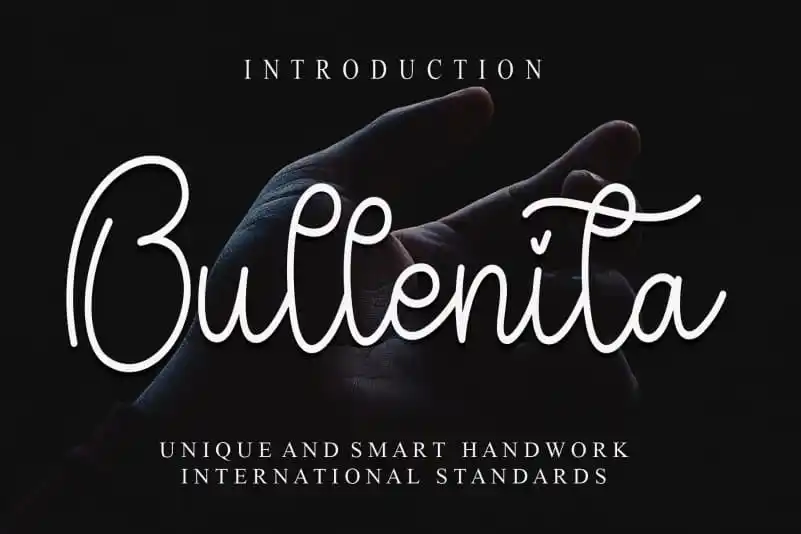
Bullenita Handwritten Font – Download Grátis
A BulleTina Handwritten Font é uma deliciosa forma de adicionar um toque único e autêntico a qualquer projeto visual. Com sua escrita elegante e suave, esta fonte oferece um toque humano que torna seus designs mais emocionantes e memoráveis. Ela foi criada pelo designer creativeletter para aqueles que buscam uma fonte de escrita real em seu trabalho gráfico. Não é apenas sobre a aparência; é também sobre a sensação de autenticidade que essa fonte provoca, tornando-a perfeita para uso em materiais pessoais e anúncios, ou até mesmo em cartões de Natal personalizados. A BulleTina oferece uma experiência única, permitindo que você destaque sua marca com um toque delicado e único.